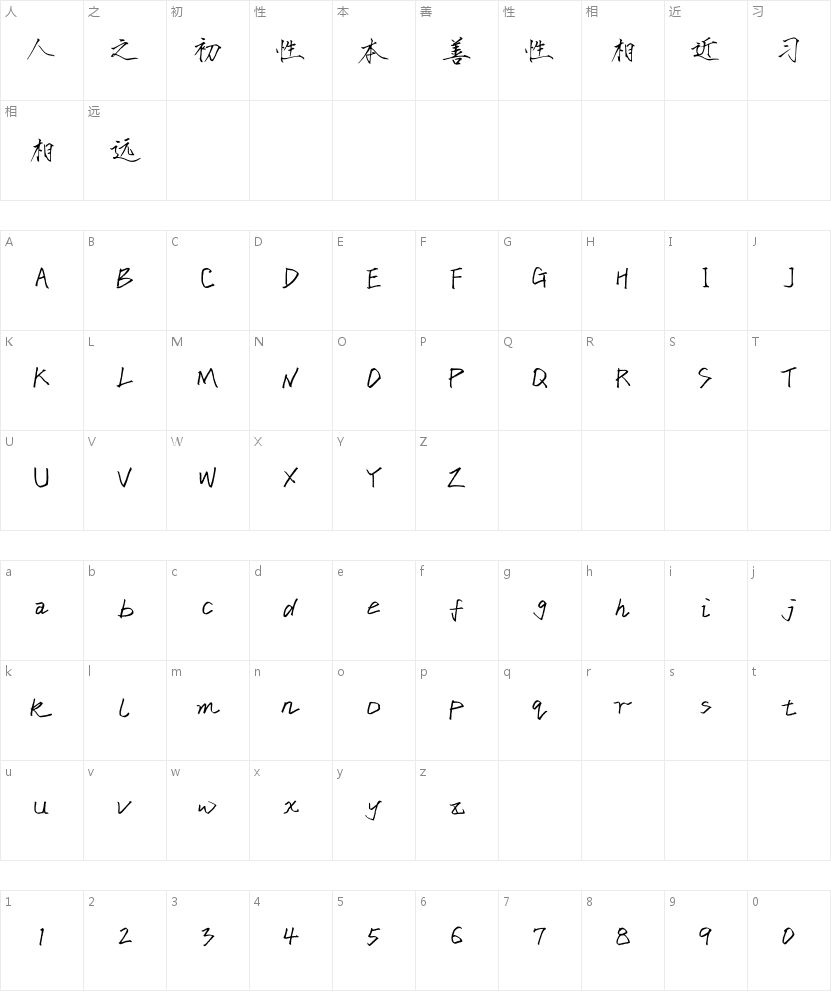
华光硬笔简瘦金体
华光硬笔简瘦金体是一种美观、简洁的中文书法字体,其特点是线条流畅、锐利、清晰,具有一种简洁、清爽、大气的感觉。此字体是基于硬笔书法的传统技巧和现代设计理念相结合而成,适用于广告、包装设计、印刷、电脑字体等众多领域。此字体的使用范围广泛,可适用于文化、商务、艺术、广告等不同领域,展现出不同的魅力和风格。
华光硬笔简瘦金体是一款非常不错的手写艺术字体,具有很好的视觉感,适合于文化类的宣传设计、商业类品牌的广告和产品包装设计以及个性化文字排版等较多场景。
华光硬笔简瘦金体字符映射图